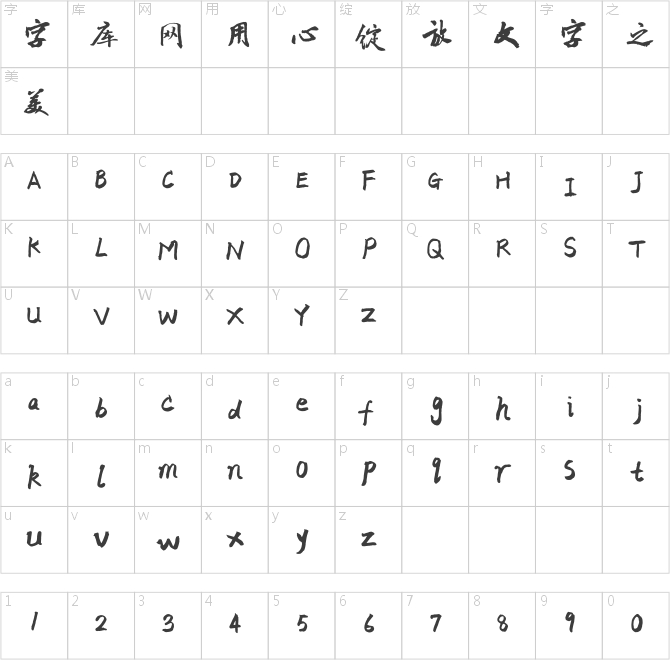
字體名稱: 桃煦古風廣告簡
桃煦古風廣告簡體
《桃煦古風廣告簡體》是一款適合視頻制作、平臺設計和辦公文稿的毛筆字體。該字體適全當今 時代閱讀和審美要求,在學習和傳承中國書法,充分發揮電腦等現代信息技術優勢,將古風古韻融入現代廣告字體,整理形成的一套適應視頻制作、平面設計和電腦方案起草的字體。主要特色如下:
一、具有古風古韻。充分汲取中國5000多年書法豐富的營養,盡力展現古人筆法、結字和墨色,發揮毛筆豐富的點畫、線條表現特色,使字體具體較強的古風古韻。
二、適應現代審美。緊跟當今時代時代發展趨勢,適應現代信息對廣告、美術等字體的需求,注重使用簡體字規范字,避免個別讀者辨認繁體字費時,日漸生疏的困惑。
三、較強使用場景。不僅是電腦上視頻制作、平臺設計和文稿處理的PC字庫,而可適用于手機和平版等電子產品,能夠在多種場景使用和運用。